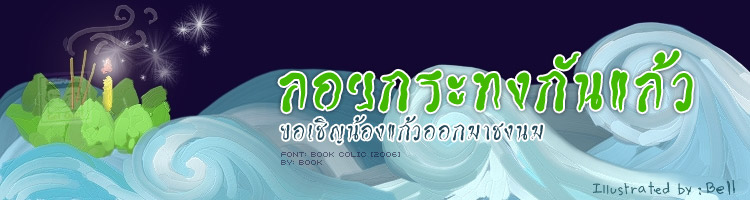
ในกระทงมีเหลี่ยม  :30:
วันคริสต์มาส :22:
วันคริสต์มาส+ปีใหม่ '๕๐  :22:
ครบรอบ1ขวบจู๋นี้ (เลยมา6วัน) :22:
ฟอนต์ก็สวยเนอะพี่หมูเนอะ :21:
สวยครับสวย คนทำก็น่าจะสวย :33: